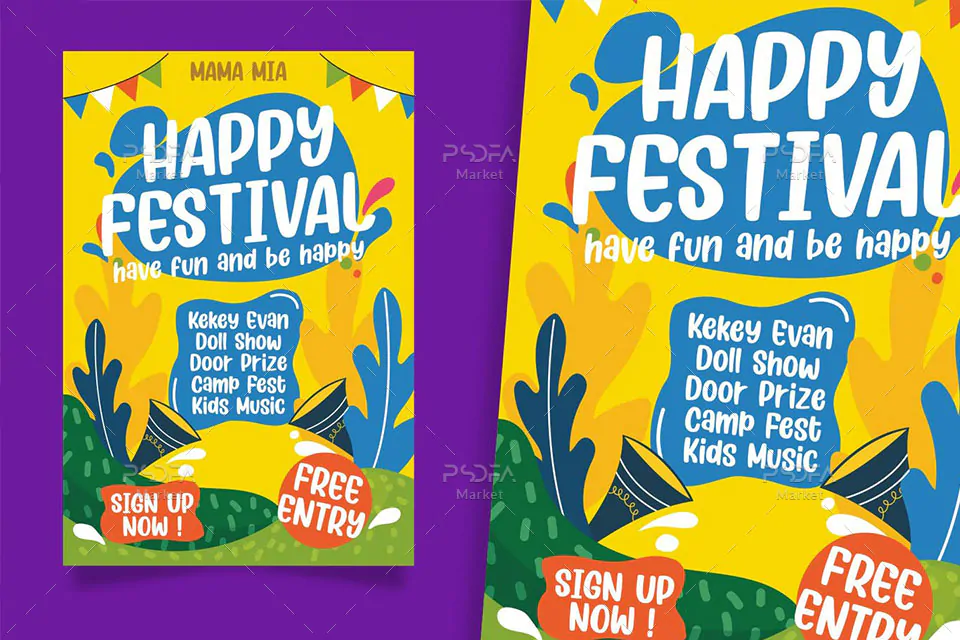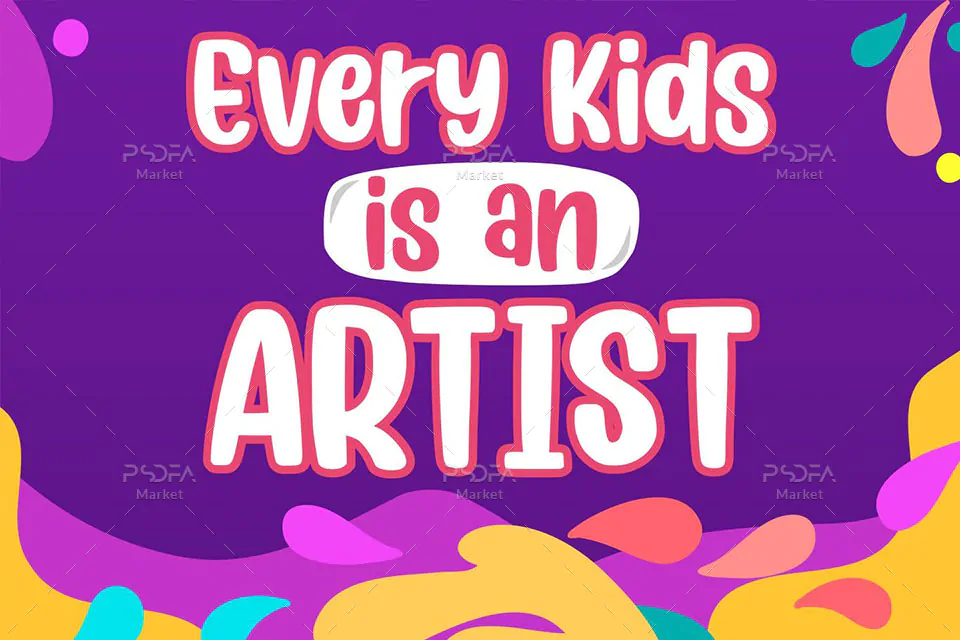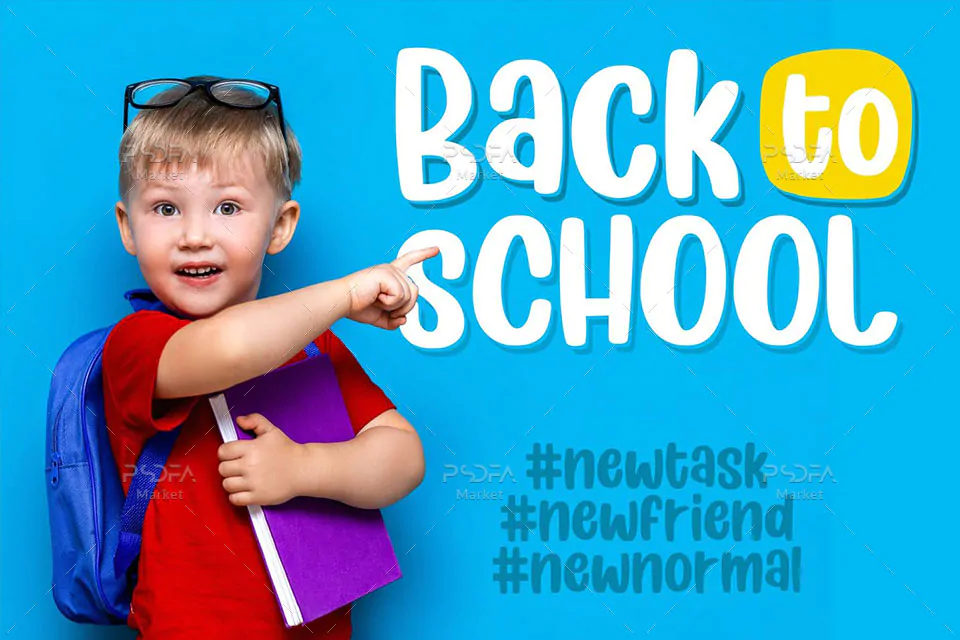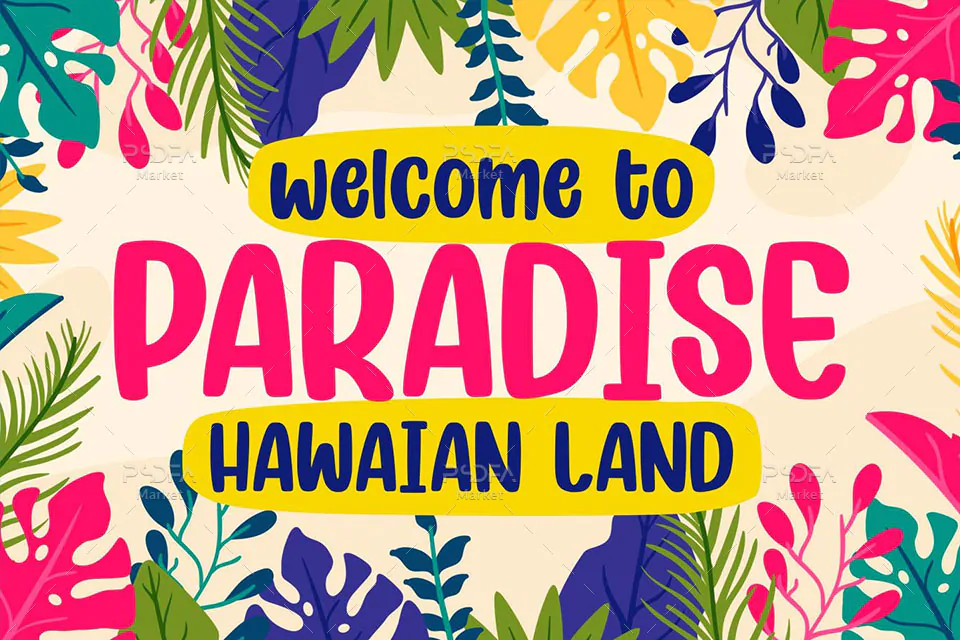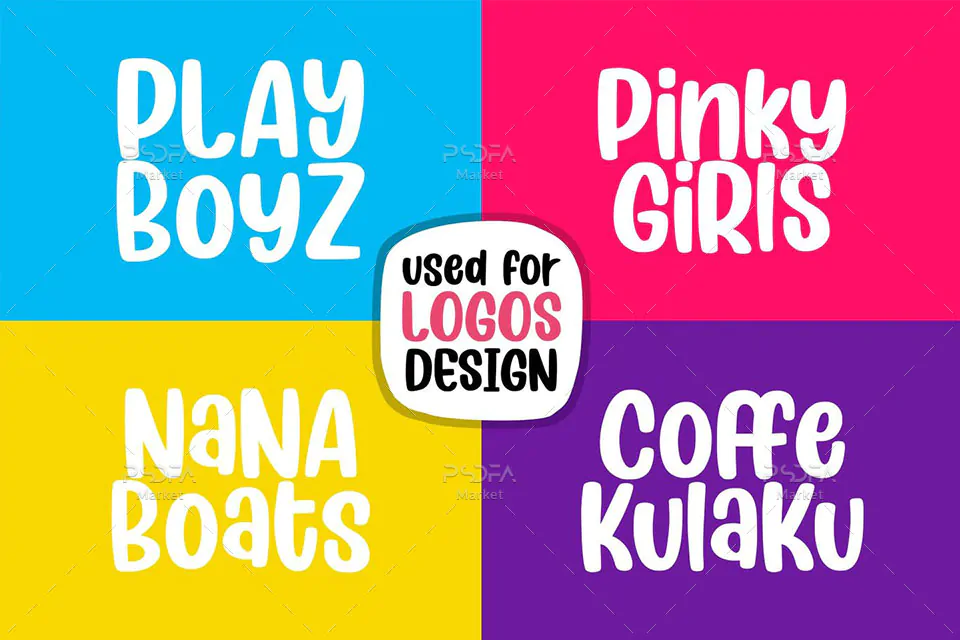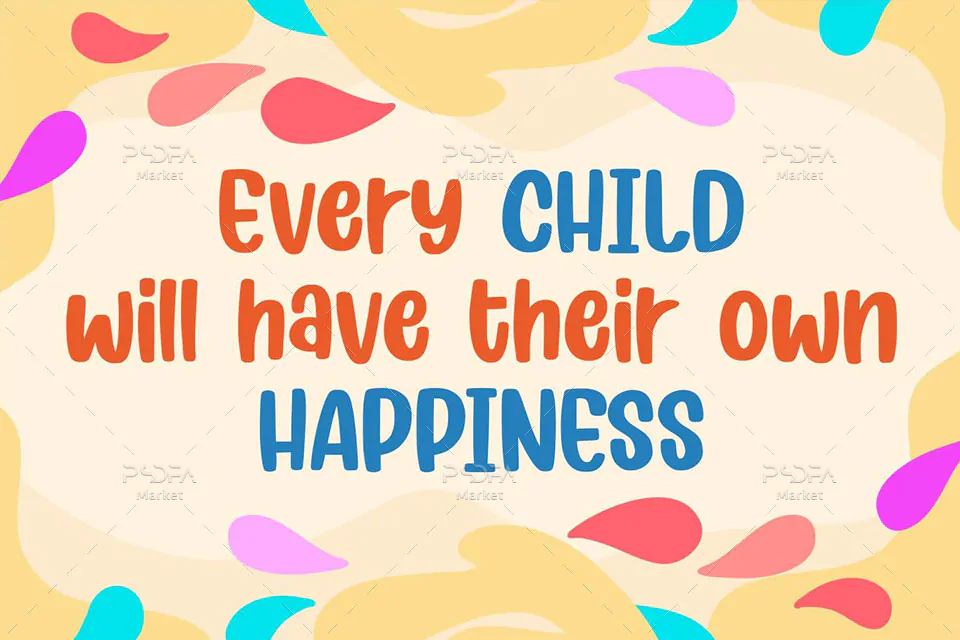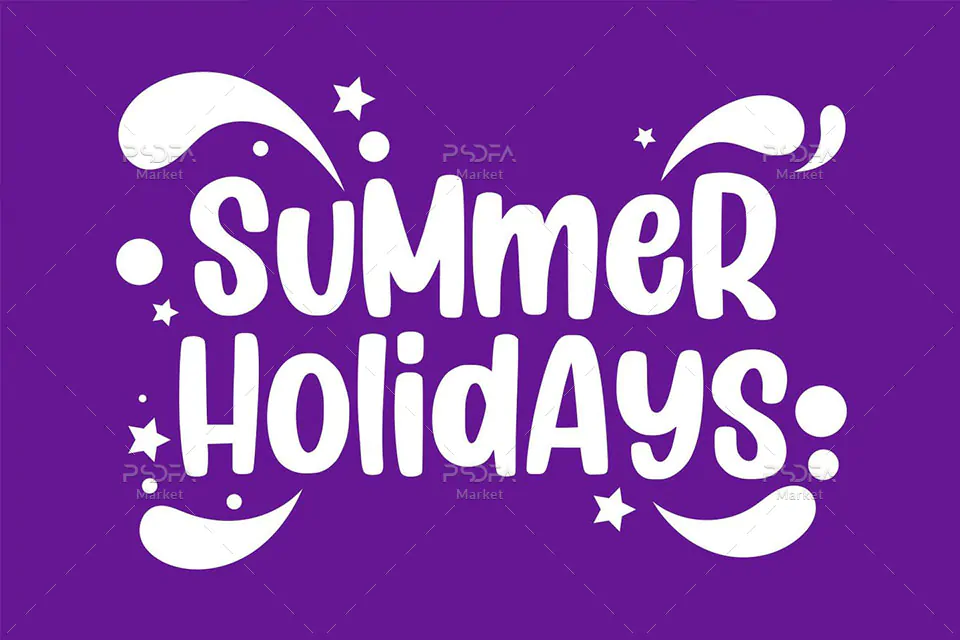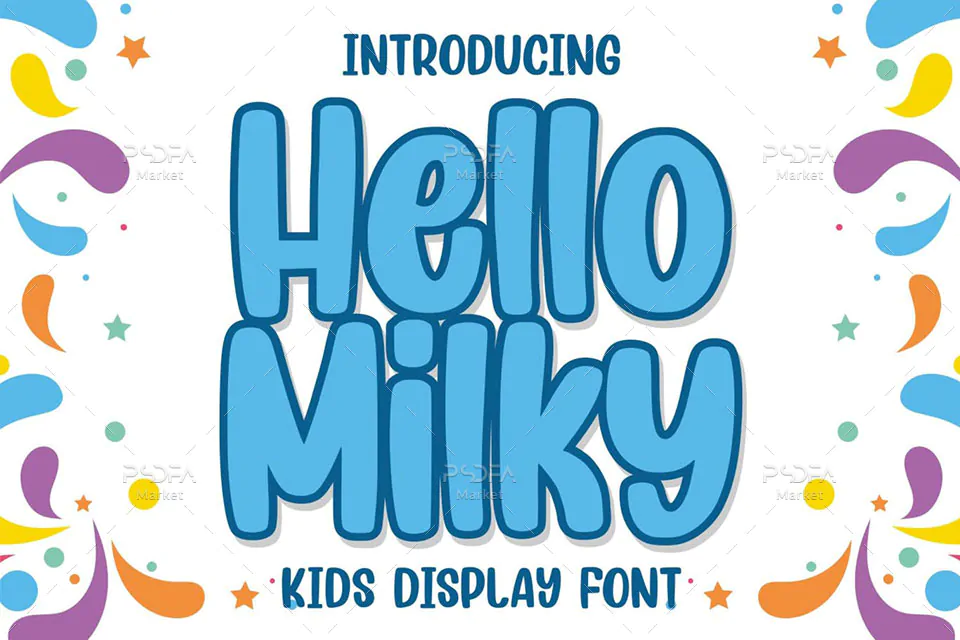
فونت نمایشی کارتونی و کودکانه Hello Milky یک قلم فوق العاده زیبا انگلیسی است که مناسب جهت استفاده در طرحهای گرافیکی مختلف به خصوص طراحی انواع تصاویر کودکانه و کارتونی میباشد. این فونت زیبا در قالب 3 فایل OTF, TTF, WOFF در فایل محصول قرار دارد که با نصب یکی از 2 فرمت ttf یا otf در پوشه فونتهای سیستم میتوانید از این فونت انگلیسی در تمام نرم افزارهای گرافیکی و تایپ متون همچون فتوشاپ، افتر افکت، پریمیر، ورد، پاورپوینت و … استفاده کنید.
فونت Hello Milky در وزن معمولی (Regular) طراحی شده است که میتوانید از آن در طراحی بسته بندی محصولات، لوازم التحریر، بگهای خرید و هدیه، ظروف یکبار مصرف، رابط گرافیکی گیم، تقویم، پوستر، بنر، بروشور، تراکت، طراحی صفحات وب و دیگر طرحهای گرافیکی استفاده کنید. از نسخه woff این قلم نیز میتوانید در طراحی صفحات وب استفاده کنید.
- نام فونت: Hello Milky